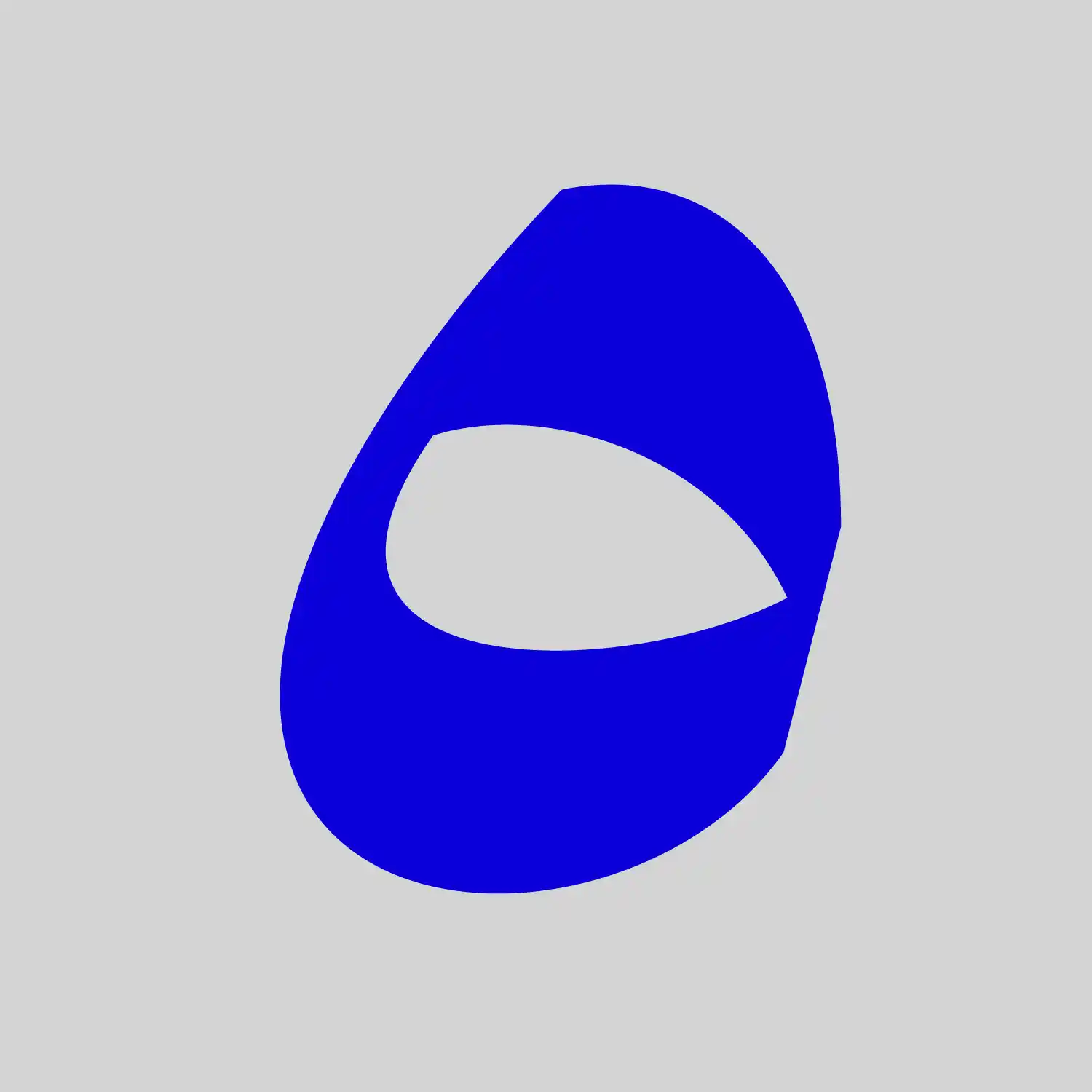
وقتی صحبت از فونت نسخ میشود، شاید تصویر ذهنی بیشتر ما فونتهای سنتی و کلاسیک باشد. اما فونت ونوو (Veno) تمام کلیشهها را میشکند. این تایپفیس با ۱۳ وزن متنوع، رویکردی مدرن به خط نسخ دارد.
چرا فونت ونوو خاص است؟
فونت ونوو یک تایپفیس فارسی و عربی در خانواده نسخ است که با رویکردی مدرن و معاصر طراحی شده. فرم کلی این فونت به ریشههای نسخ وفادار مانده، اما ویژگیهای بصری و تنوع وزنهای آن باعث شده به یکی از مدرنترین فونتهای نسخ بازار تبدیل شود.
داشتن ۱۳ وزن مختلف — از Thin فوقالعاده نازک گرفته تا Black بسیار ضخیم — به طراحان این امکان را میدهد که در یک پروژه، از یک خانواده فونت واحد برای تیتر، زیرتیتر، متن اصلی و حتی کپشن استفاده کنند. این انسجام بصری، یکی از اصول طراحی گرافیک حرفهای است.
۱۳ وزن فونت ونوو — از Thin تا Black
تنوع وزنها در فونت ونوو بینظیر است. شما میتوانید:
- از وزنهای نازک (Thin, Light) برای طراحیهای مینیمال و مدرن استفاده کنید.
- وزنهای متوسط (Regular, Medium) را برای متنهای اصلی و پاراگرافها به کار ببرید.
- وزنهای ضخیم (Bold, ExtraBold, Black) را برای تیترها و عناصر برجسته انتخاب کنید.
فونت ونوو برای چه پروژههایی مناسب است؟
- طراحی وبسایت و اپلیکیشن: خوانایی بالا و تنوع وزن، ونوو را به گزینهای عالی برای طراحی رابط کاربری تبدیل کرده است.
- برندینگ و هویت بصری: یک خانواده فونت کامل برای تمام نیازهای برند — از لوگو تا کاتالوگ.
- طراحی مجله و نشریه: انسجام بصری در تیتر، لید و متن اصلی با یک خانواده فونت.
- پوستر و بنر تبلیغاتی: وزنهای ضخیم برای تیترهای جذاب و چشمگیر.
- محتوای شبکههای اجتماعی: طراحی پست و استوری با ظاهری حرفهای و یکپارچه.
مقایسه فونت ونوو با سایر فونتهای نسخ
در مقایسه با فونت تحریر (که برای کتاب و متنهای طولانی طراحی شده) و فونت تجرید (که برای وب و نمایشگر بهینه شده)، فونت ونوو با ۱۳ وزن خود، منعطفترین گزینه برای پروژههای متنوع است.